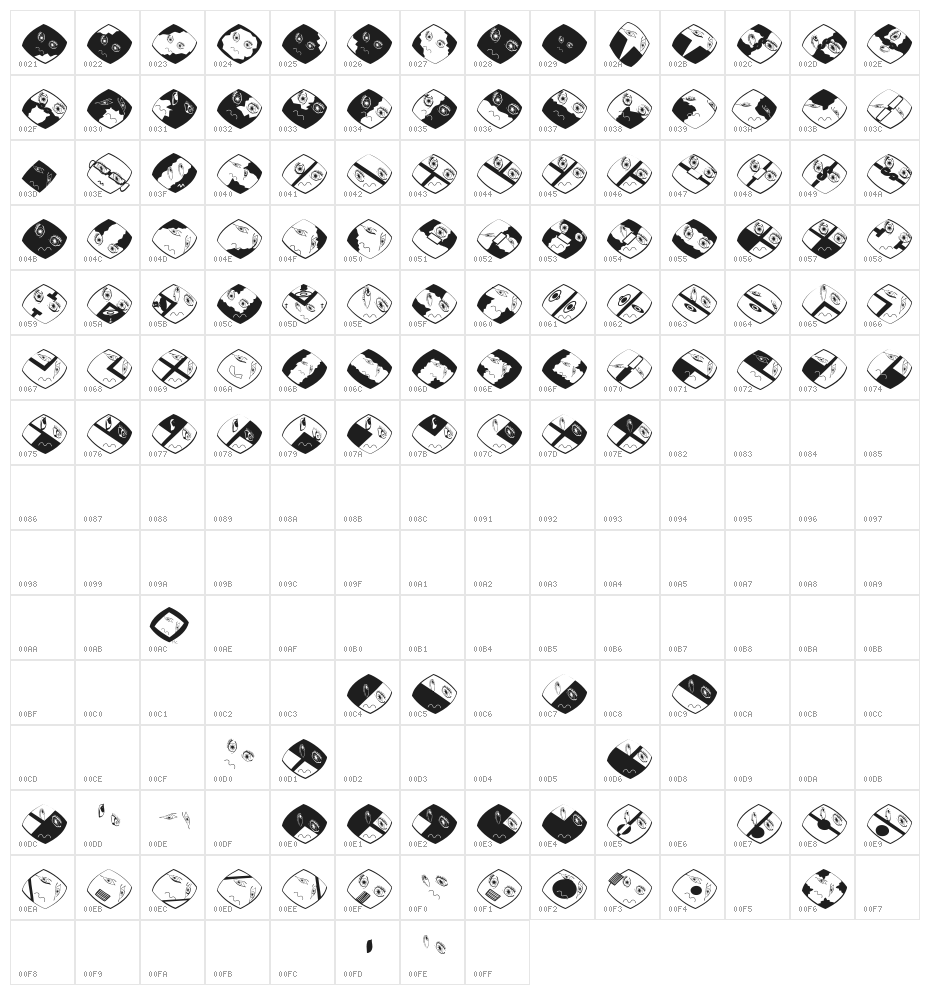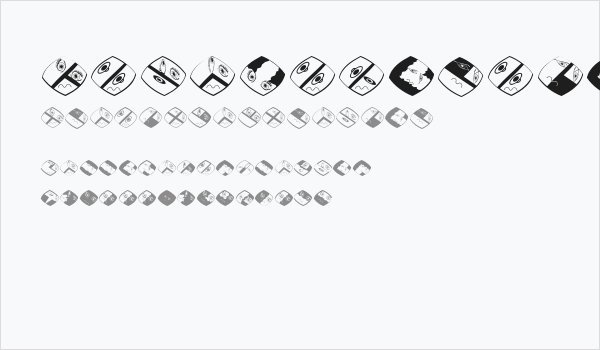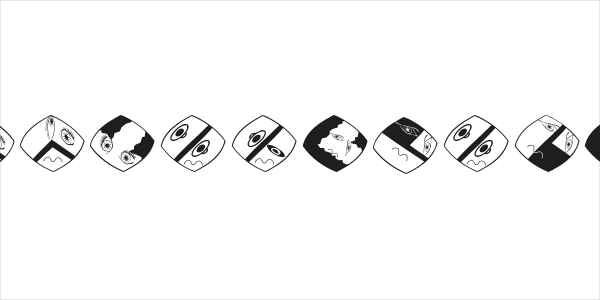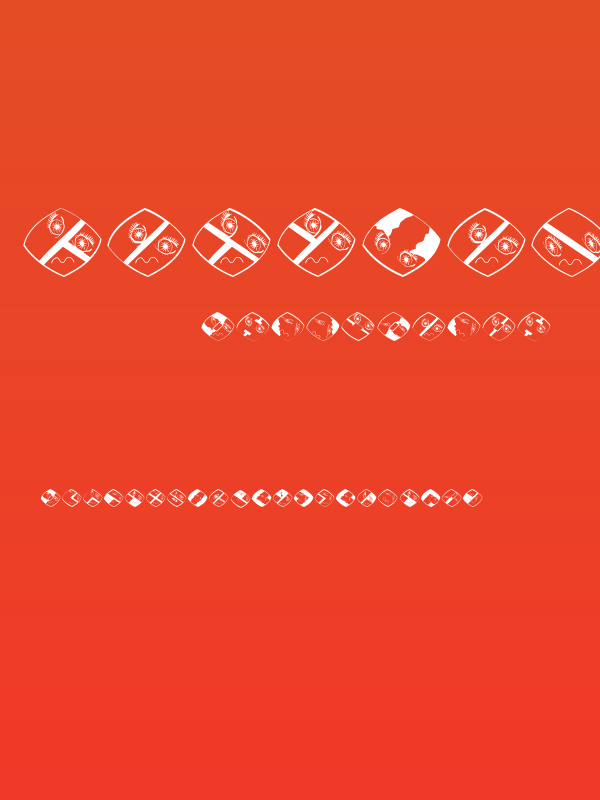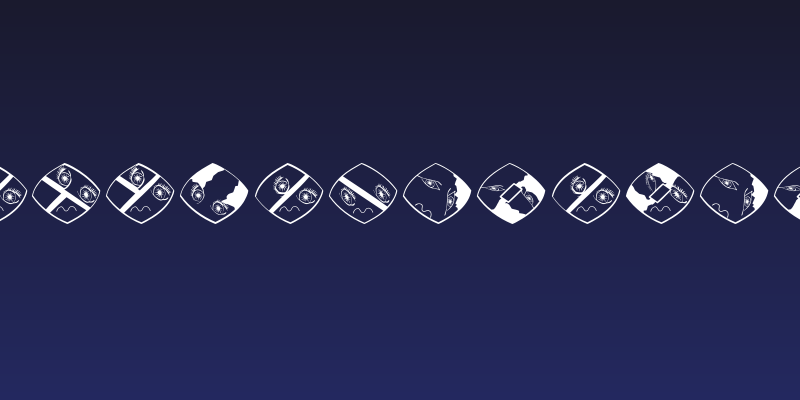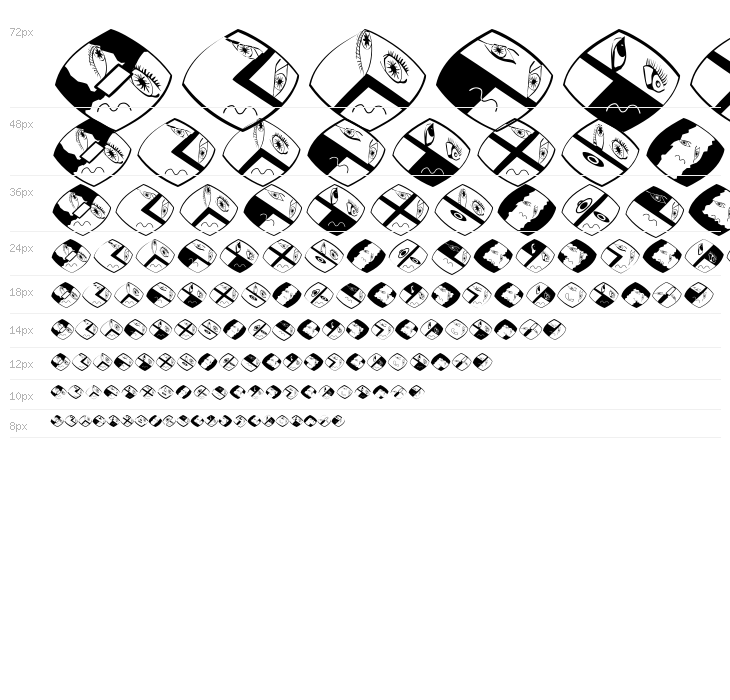
FaceLaboratory Font
| Stile generale | Artistic, Abstract |
| Caso d'uso | Art projects, Decorative elements |
| Progetti proposti | This design could be used for art projects, creative illustrations, or as a decorative element in graphic design, but not for standard text applications. |